Y no penséis que hoy bajamos el nivel, porque para nada, puesto que tenemos el placer de poder entrevistas a Jackson Alves .
Aunque series pocos los que no sabrĂ©is quiĂ©n es este gran calĂgrafo, os cuento que Jackson es uno de los mayores representantes de la caligrafĂa a nivel global ya que su Brasil natal pronto se le quedĂł pequeño y decidiĂł compartir su trabajo y su conocimiento por multitud de paĂses:
CuĂ©ntanos, ¿dĂłnde naciĂł el interĂ©s por la caligrafĂa?, ¿Con quĂ© edad empezaste a profundizar en este hermoso mundo?
Siempre me han gustado las letras, pero yo aprendĂ caligrafĂa hace solo 5 años, cuando yo tenĂa 33.
Lettering, sign painting, caligrafĂa, ilustraciĂłn... ¿En quĂ© campo te sientes más cĂłmodo trabajando y quĂ© diferencias encuentras entre un tipo de trabajo y otro?
Primero lettering, segundo caligrafĂa, y sing painting en tercer lugar. No me gusta decir que hago ilustraciĂłn hoy en dĂa. Considero que realizo "diseño de letras" y mezclo las diferentes tĂ©cnicas siempre que puedo.
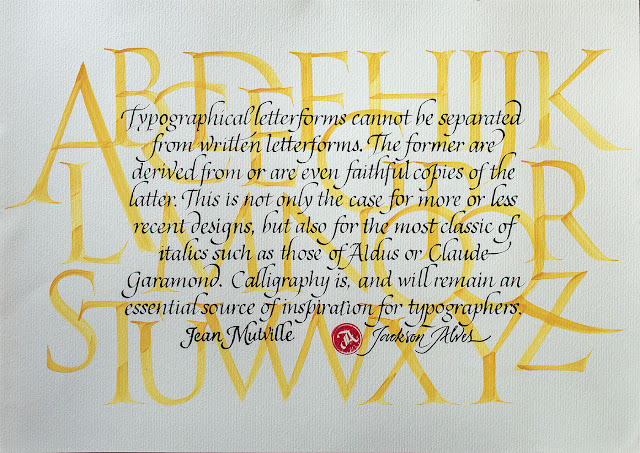
En tu cartera de proyectos podemos ver obras para EE.UU., Reino Unido, Rusia o Australia ¿CĂłmo llegaste a trabajar para clientes de todo el mundo?, ¿QuĂ© medio crees que es más eficiente para conseguir nuevos clientes, correo electrĂłnico, un sitio web propio, las redes sociales (Twitter, Facebook ...) o redes creativas como Behance?
Los medios sociales siempre me ayudaron a conseguir nuevos clientes, pero creo que Behance ha sido el portal que más me ayudado a captar nuevos clientes.
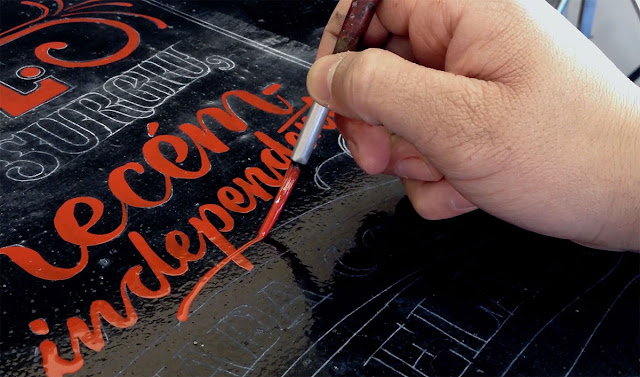
Como decimos has trabajado con clientes de muchas partes del mundo, ¿has notado mucha diferencia a la hora de trabajar con clientes de un paĂs u otro? Con quĂ© clientes te sientes más cĂłmodos?
En realidad, no he podido apreciar mucha diferencia. Tal vez los brasileños son más negociantes…
El lettering parece atraer mucho interĂ©s en los Ăşltimos años, ¿A quĂ© crees que es debido? ¿Has notado un aumento en el nĂşmero de clientes o asistentes a los talleres que impartes?
Creo que todo el mundo es capaz de ver esto. Tal vez las personas simplemente están cansadas de ver Helvética por todos lados.
Esto no es un problema del lettering, creo que a veces una buena tipografĂa es suficiente, pero la mayorĂa de la gente no sabe realmente de la importancia de comprar una fuente.
Pero en algunas ocasiones, cuando se puede ver el toque humano en un proyecto este luce mucho mejor.
Podemos ver que has realizado talleres por todo Brasil, San Francisco, Nueva York ... ¿Crees que el interĂ©s por la caligrafĂa en todo el mundo es una moda o es un interĂ©s real a largo plazo? ¿QuĂ© diferencias has notado en los estudiantes de los diferentes paĂses que has visitado? ¿Tienen diferentes inquietudes acerca de la letra?
Creo que la mayorĂa de las personas interesadas se aferran a una moda pasajera, pero puedo ver en algunos estudiantes una verdadera pasiĂłn dentro de ellos, y puedo apreciar claramente cĂłmo esta persona nunca dejará de lado la práctica de la caligrafĂa.
Creo que los estudiantes que he tenido hasta ahora son muy similares. En cada clase me encuentro con un montĂłn de principiantes y algunas personas que ya han se han sumergido antes en el mundo de la caligrafĂa.
En unas pocas semanas iniciarás un tour en el que impartirán talleres por Estados Unidos y Europa, ¿quĂ© esperas de encontrar en estos nuevos talleres?
Esto no es un verdadero tour, publiquĂ© algunas ciudades en las que conozco a alguien y tal vez pueda ir a impartir algĂşn taller. Va a depender de las personas que estĂ©n interesadas en cada uno de los posibles lugares. Pero, espero grandes estudiantes, ¡he conocido a tanta gente agradable en mis talleres! ¡Amo hacer esto!
Pronto tu curso de caligrafĂa estará disponible online a travĂ©s Skillshare ¿QuĂ© opinas de la posibilidad que el entorno online ofrece para compartir conocimientos?
Recibo muchos mensajes de personas de todo el mundo pidiendo que vaya a sus paĂses para realizar talleres, pero claro, no puedo ir a todos los lugares. AsĂ que creo que la plataforma online es una gran manera de compartir conocimiento.
Hasta aquĂ la entrevista de hoy con nuestro querido amigo Jackson Alves, ¿que os ha parecido? ¿QuĂ© os ha llamado la atenciĂłn? Como siempre, nos encantarĂa recibir vuestros comentarios debajo de este articulo con vuestras impresiones.